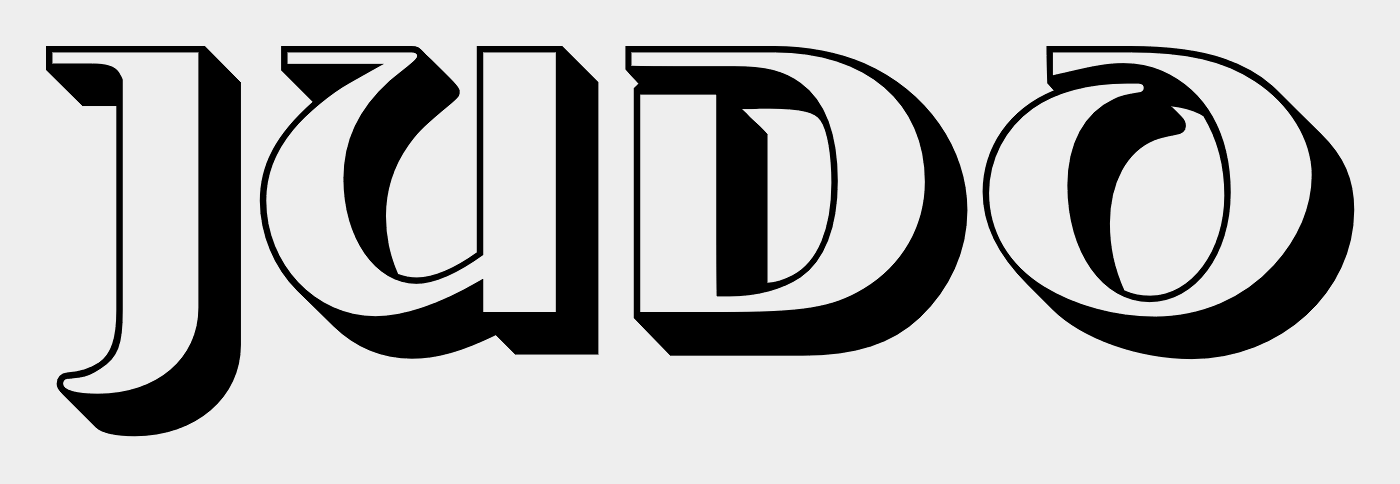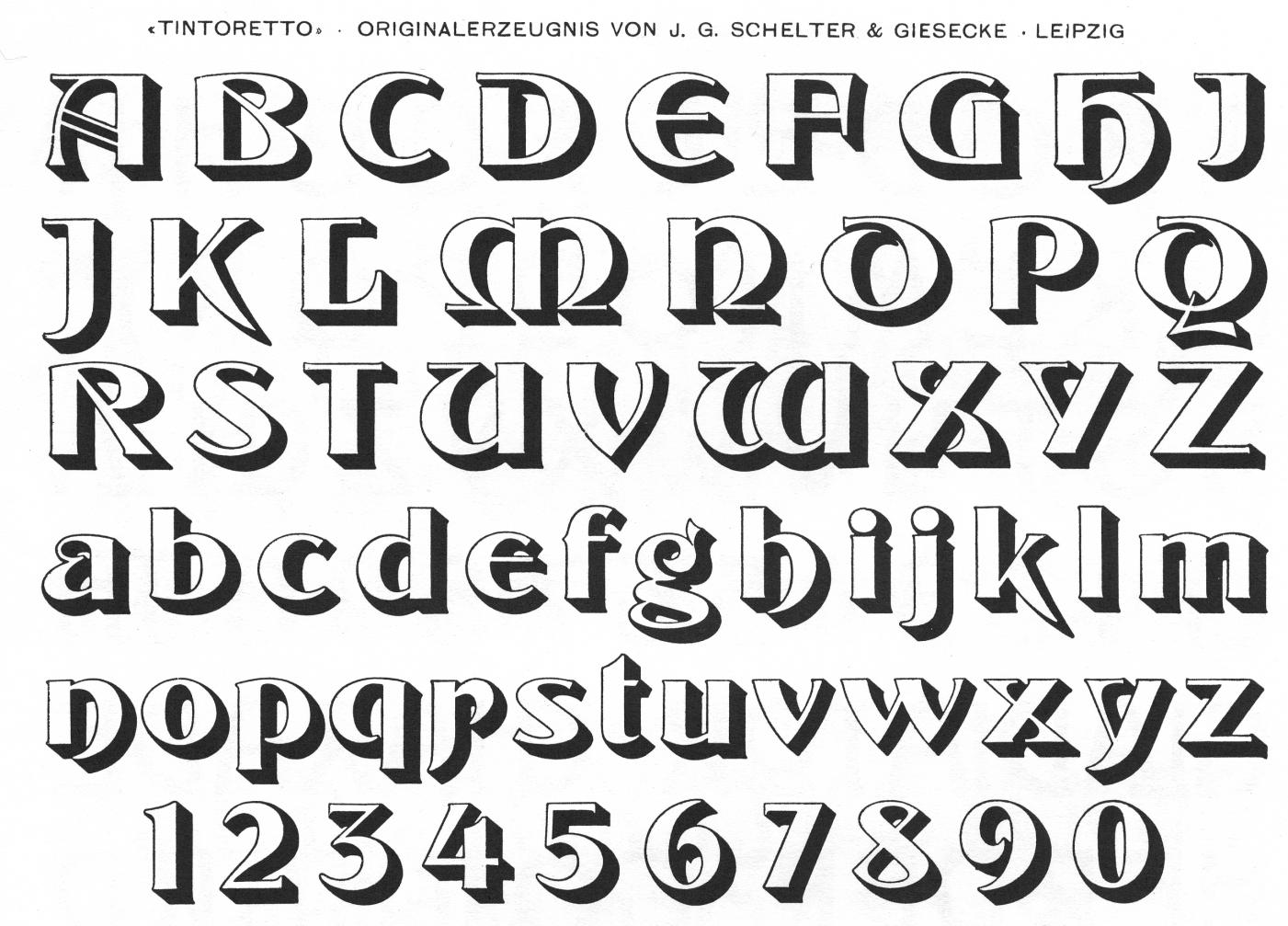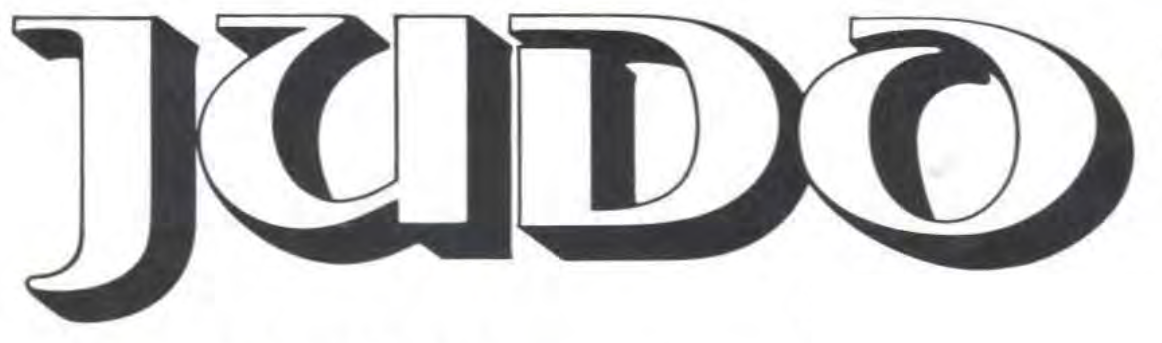
Britisches JUDO-Magazin Logo gesucht
ohne eine geopolitische Diskussion (ob nun DDR oder BRD) vom Zaun zu brechen, bitte ich um Identifikationshilfe bei der Suche nach der Schriftart, welche als Logo für das britische Judomagazin verwendet wurde.
Der Ausschnitt stammt von der Ausgabe 1984. Mehr kann ich leider nicht liefern.
Deine Vorlage ist in Details unterschiedlich zur Tintoretto von Ralph Unger aus 2006 – damals hieß sie ebenfalls so.
Ich weiß auch nicht so ganz, ob die nicht mit der Hand gezeichnet wurde. Sie sieht fast so aus. Ist aber von 1984 und nicht von 2006. Deshalb kann sie damals angepasst worden sein. Das "D" wird ja vom "O" verdeckt, was so damals wohl nur manuell möglich war.
Es gab sie auch von Letraset, damit war dein gesuchtes JUDO leicht herzustellen.
At the end of the 19th century, Schelter & Giesecke released a series of bicolor typefaces. The basic shadow style was named Plantin. It could be combined with a fill style named Murillo. This bicolor package was marketed as Donatello. It was accompanied by a third style, Bramante, which is pre-filled with a shade.
Plantin was further available with a couple of additional alternate letterforms like an uncial E, e, M, N, a round-bottomed V and W, an A with an angled double bar, or an R with a leg that starts at the top of the stem. This set (with shadow) was called Virgil. It could be filled with the corresponding Aldo Manutio. Together, Virgil and Aldo Manutiowere known as Tintoretto. The peculiar alternates were also available for the hatched Bramante, resulting in Buonarroti.
Tintoretto (actually Virgil) was revived in the 1970s as a Letraset typeface. There are various sloppily digitized versions available for free on the net, both of the fill (by Dieter Steffmann) and the shadow version. In 2006, Profonts did a less limited commercial version, consisting of Tintoretto Outline (i.e. Virgil) and Tintoretto Fill (i.e. Aldo Manutio).